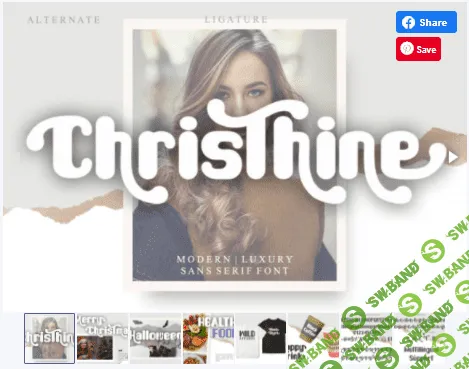
Название: Christhine Font (2021)
Christhine — классный шрифт с интересным дизайном. Это поднимет широкий спектр идей для крафта, от карт до брендинга, этикеток и многого другого. Этот шрифт имеет кодировку PUA, что означает, что вы можете легко получить доступ ко всем глифам и росчеркам!